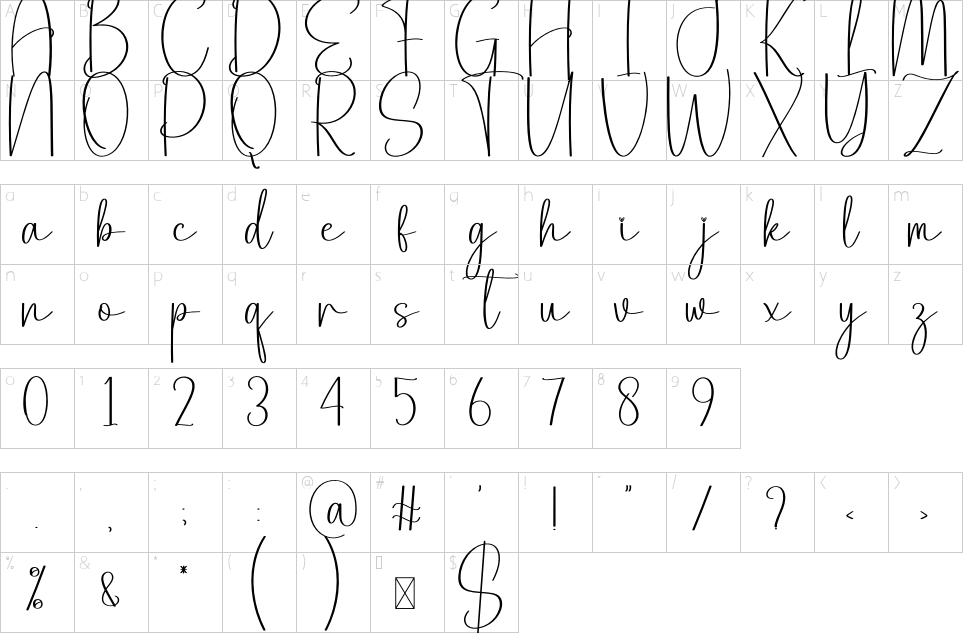
Descubra a fonte gratuita ‘Activity Font’, projetada por scratchones e disponível tanto para Windows quanto para Mac. Esta elegante fonte foi projetada para quem busca um estilo limpo e fácil de ler em seu projeto digital. Com seu design minimalista e clean, a fonte ‘Activity’ se adequa perfeitamente a qualquer layout gráfico ou design web. Se você está procurando por uma fonte moderna e versátil que não se sobrecarregue com excessos, a ‘Activity Font’ é uma escolha ótima. Atualmente, esta fonte foi baixada 488 vezes, o que é uma indicação de sua popularidade entre os designers e criativos digitais. Experimente a ‘Activity Font’ hoje e veja como ela pode refinar seus projetos.